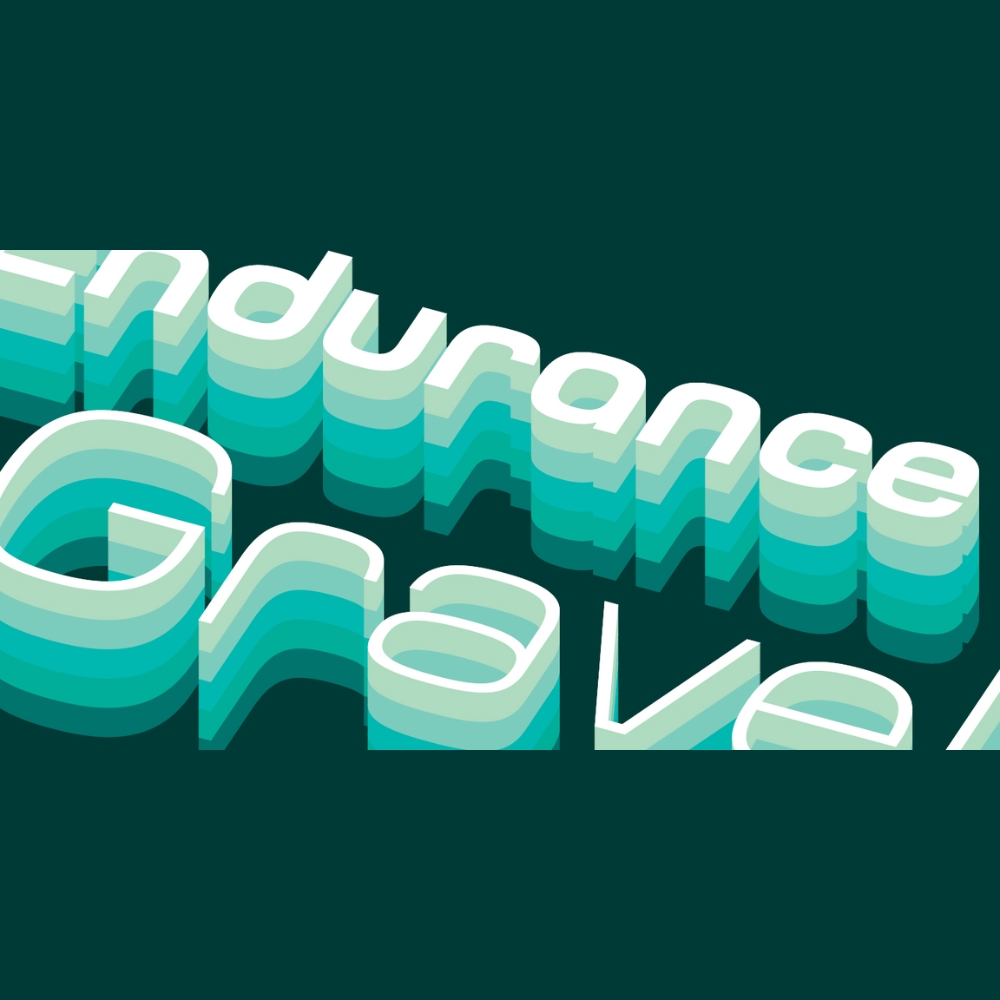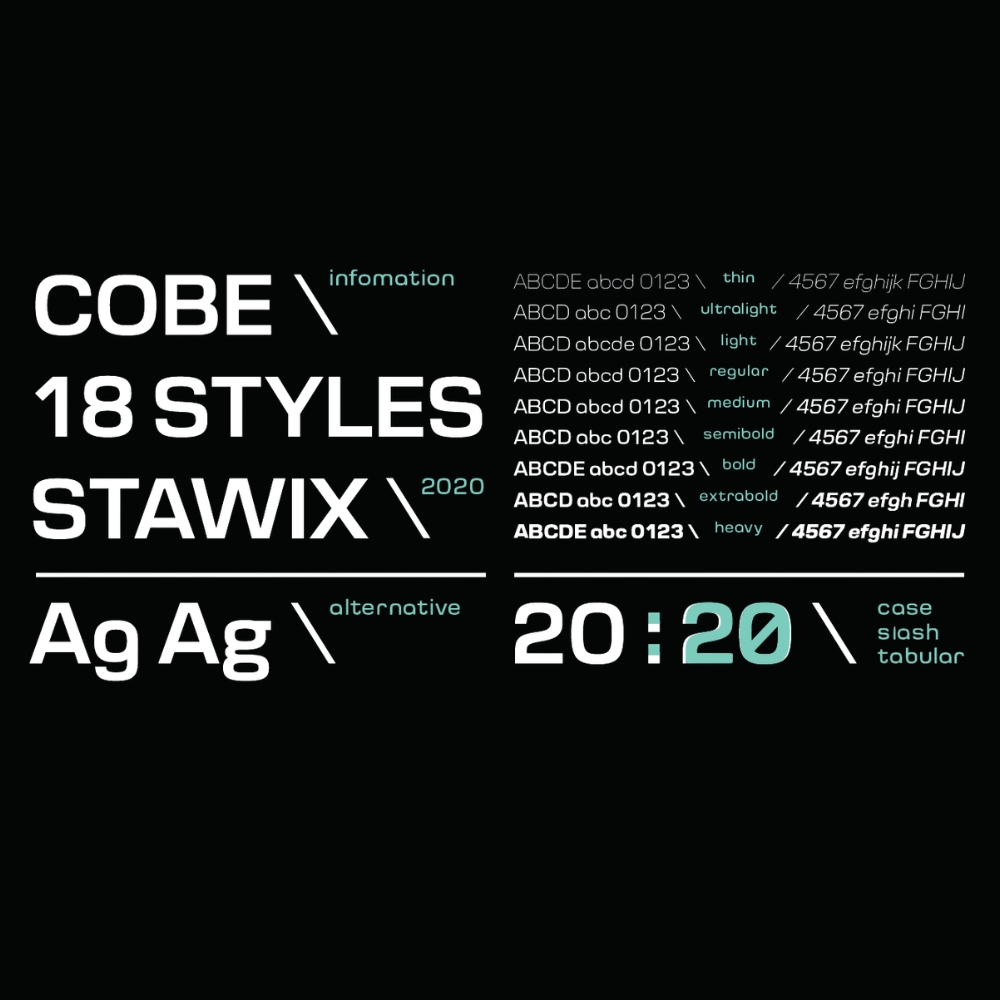
Font việt hóa cobe là font chữ sans-serif hiện đại với phong cách geometric tròn trịa, thân thiện được sử dụng trong thiết kế bao bì sản phẩm trẻ trung, túi giấy startup và in ấn cho thương hiệu minimalist. Font chữ tiếng việt cobe sans serif mang nét chữ mềm mại, dễ đọc phù hợp cho nhiều ngành hàng.
Font Cobe Sans Serif là gì?
Font Cobe là font chữ sans-serif hiện đại thuộc nhóm geometric với đặc điểm các góc bo tròn nhẹ, tạo cảm giác thân thiện, dễ tiếp cận nhưng vẫn đủ chuyên nghiệp. Font này mang phong cách minimalist, sạch sẽ, phù hợp với xu hướng thiết kế hiện đại.
Đặc điểm của font Cobe:
• Geometric với góc bo tròn: Cobe được xây dựng dựa trên hình học cơ bản (tròn, vuông) nhưng các góc được bo tròn nhẹ, tạo sự mềm mại.
• Thân thiện, trẻ trung: Phong cách rounded geometric tạo cảm giác gần gũi, phù hợp thương hiệu hướng đến giới trẻ, startup, lifestyle.
• Minimalist, sạch sẽ: Nét chữ đơn giản, không cầu kỳ, tạo cảm giác hiện đại, chuyên nghiệp.
• Hỗ trợ tiếng Việt: Font việt hóa hỗ trợ đầy đủ dấu thanh tiếng Việt.
Font Việt hóa Cobe thường có các phiên bản:
• Cobe Regular (400) – cho body text
• Cobe Medium (500) – cho tiêu đề phụ
• Cobe Bold (700) – cho logo, tiêu đề chính
Font chữ tiếng Việt Cobe Sans Serif hiện đại, dễ đọc và rõ ràng
Font Cobe là lựa chọn hiện đại với thiết kế sans-serif gọn gàng, phù hợp nhiều nhu cầu thiết kế và in ấn. Dưới đây là bảng thông tin font Cobe Sans Serif:
Phiên bản
Font weight
Ứng dụng in ấn
Cobe Regular
400 Thông tin sản phẩm, mô tả trên bao bì.
Cobe Medium
500 Tên sản phẩm, tiêu đề túi giấy.
Cobe Bold
700 Logo startup, slogan chính.
Ứng dụng của font Việt hóa Cobe
Font có phong cách Cobe (rounded geometric) được ưa chuộng trong nhiều ngành:
• Phù hợp thương hiệu trẻ trung, thân thiện: Góc bo tròn tạo cảm giác gần gũi, dễ tiếp cận, phù hợp startup, brand Gen Z, sản phẩm lifestyle.
• Minimalist nhưng không lạnh lùng: Khác font geometric cứng nhắc, Cobe-style vẫn minimalist nhưng ấm áp hơn nhờ nét tròn.
• Dễ đọc, chuyên nghiệp: Mặc dù thân thiện, font vẫn đủ chuyên nghiệp cho thương hiệu muốn tạo niềm tin.
• Kết hợp tốt với màu pastel: Font Cobe-style hài hòa với palette màu nhẹ nhàng: pastel pink, mint, peach, lavender.
Font kiểu Cobe xuất hiện trong nhiều sản phẩm in ấn:
• Bao bì sản phẩm trẻ trung: mỹ phẩm natural, thực phẩm organic, đồ uống healthy.
• Túi giấy startup: công ty công nghệ trẻ, app, platform, SaaS.
• Logo cafe, bakery: phong cách minimalist, friendly, approachable.
• Nhãn sản phẩm handmade: xà phòng thủ công, nến thơm, skincare natural.
• Bao bì đồ chơi trẻ em: sản phẩm educational, Montessori, eco-friendly.
• Hộp quà tặng: gift box minimalist, subscription box.
• Menu quán ăn healthy: salad bar, smoothie shop, vegan restaurant.
• Catalogue sản phẩm lifestyle: wellness, yoga, meditation, self-care.
Font Cobe đơn giản, phù hợp nhiều ấn phẩm
2. Font nào giống Cobe nhất và miễn phí?
Nunito từ Google Fonts giống Cobe nhất (90%), với 14 weight từ ExtraLight đến Black, hỗ trợ tiếng Việt đầy đủ và hoàn toàn miễn phí.
3. Font rounded dùng cho sản phẩm nào?
Font rounded như Cobe phù hợp cho sản phẩm organic, startup công nghệ, cafe minimalist, bakery friendly, mỹ phẩm natural, đồ chơi trẻ em educational.